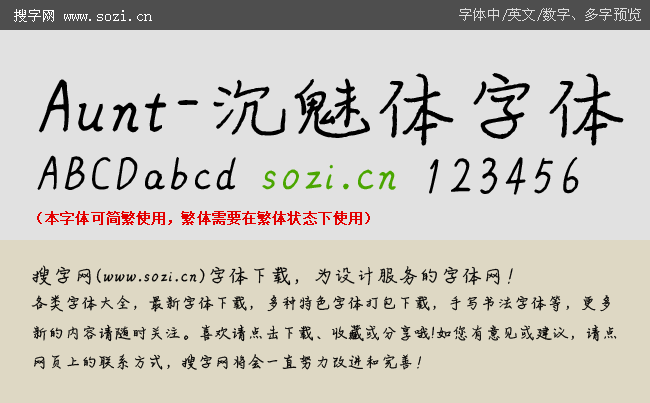
沉魅體字體
搜字網(wǎng)給大家提供一款手寫(xiě)風(fēng)格的沉魅體字體手機(jī)中文字體下載。這款手機(jī)字體是一款手寫(xiě)風(fēng)格硬筆行書(shū)書(shū)法字體,字體書(shū)寫(xiě)流暢,瀟灑大方,特別適合喜歡書(shū)法的朋友在手機(jī)上安裝使用。
- 風(fēng)格類(lèi)別: 手寫(xiě)書(shū)法體